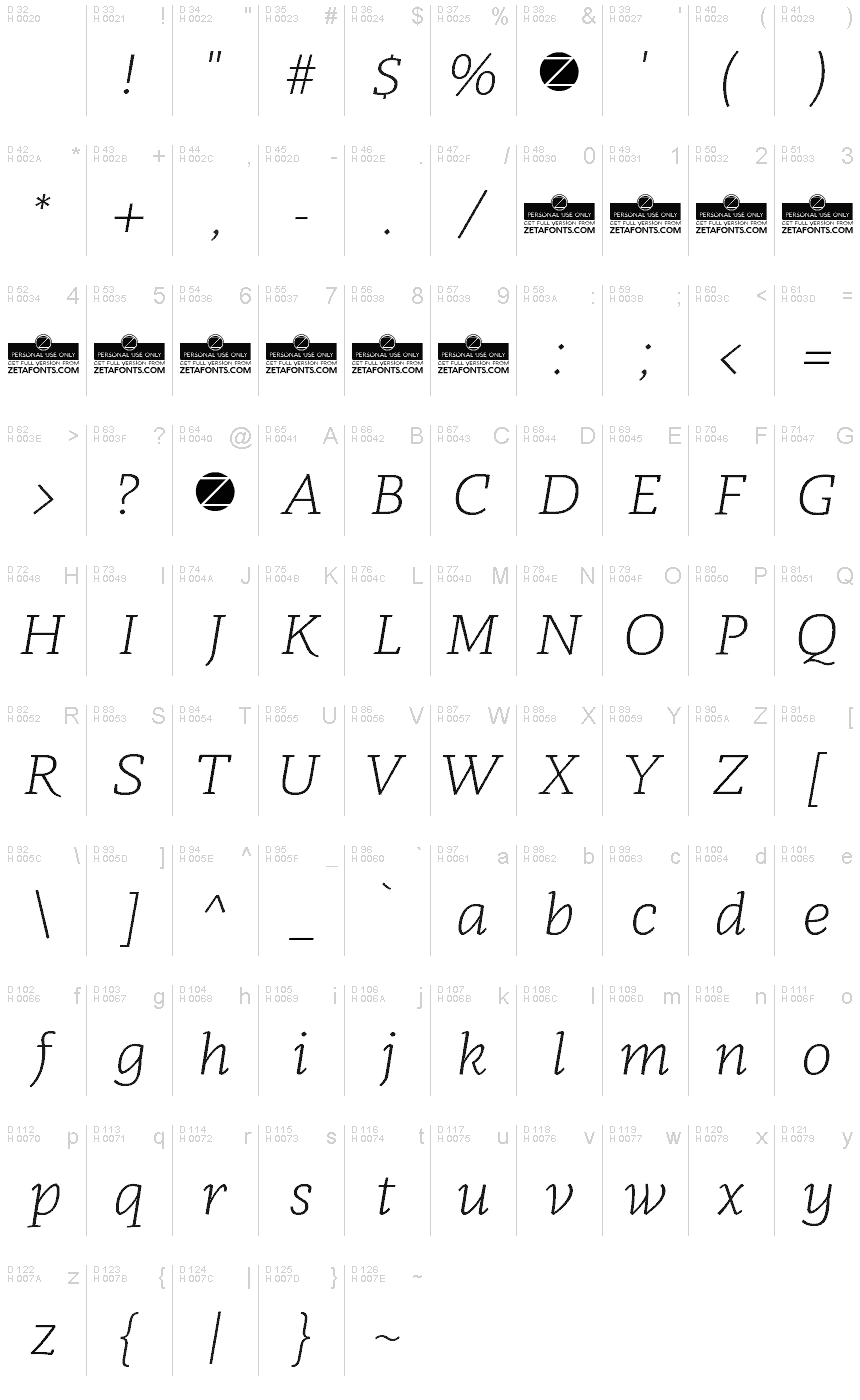
Radcliffe to rodzina krojów pisma zaprojektowana w 2018 roku przez Cosimo Lorenzo Pancino i Andreę Tartarelliego, będąca reinterpretacją klasycznego stylu Clarendon w poszukiwaniu „współczesnego klasycznego” wyglądu. Zaprojektowana z myślą o elegancji, Radcliffe wyróżnia się mocnymi szeryfami z nabehem, pionowym naciskiem i niskim kontrastem, uszlachetnionymi humanistycznym akcentem i kaligraficznym podejściem, widocznym w kursywach.
Jako krój przeznaczony głównie do nagłówków, z szeroką gamą precyzyjnie dostrojonych wag do zastosowań redakcyjnych i projektowania logo, Radcliffe jest uzupełniony o Radcliffe Text, opracowany w pięciu wagach z większą wysokością x i nieco zwężonymi proporcjami, co zapewnia maksymalną czytelność w długich tekstach na stronach internetowych i przy małych rozmiarach.
Rodzina zawiera również dwie oryginalne wagi Radcliffe Casual, zaprojektowane z estetyką kontrastu wstecznego, idealne do mniej formalnych zastosowań. Wszystkie fonty z rodziny Radcliffe obejmują pełne funkcje OpenType z alternatywami stylistycznymi, ligaturami uznaniowymi, pozycyjnymi formami cyfr, formami swash (w kursywach) oraz pełnym wsparciem dla ponad 70 języków używających alfabetu łacińskiego i cyrylicy.